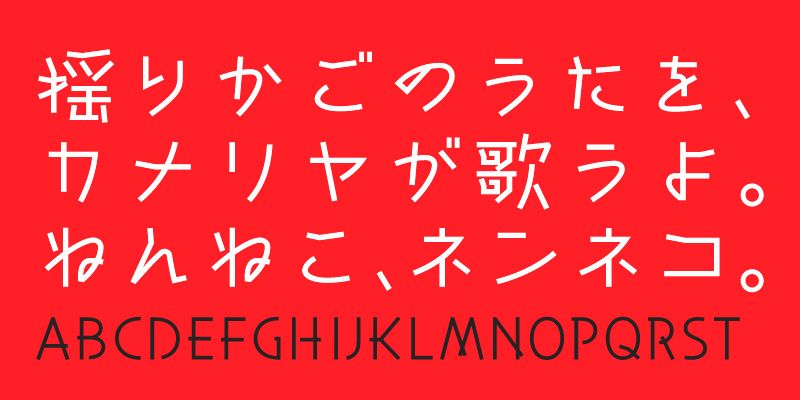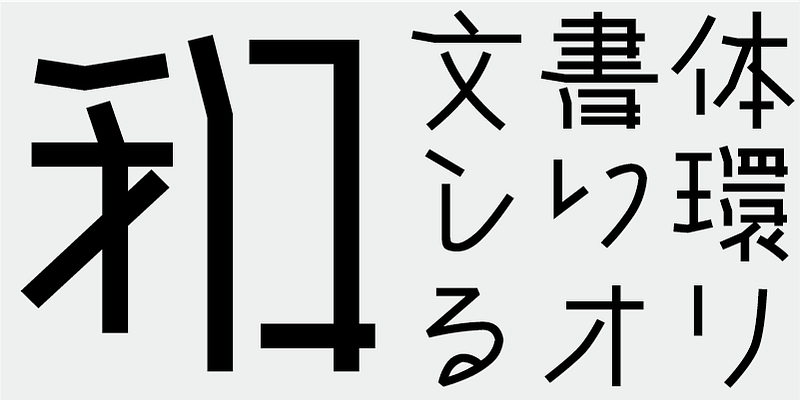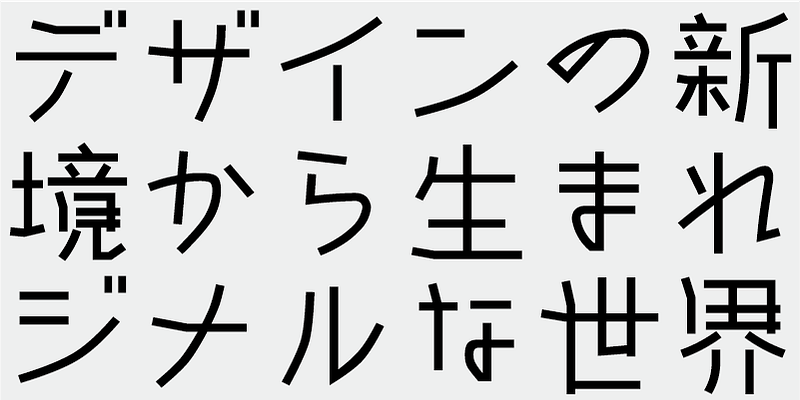
Este tipo de letra tiene un aspecto lineal y está basado en la sensación de los trabajos de mosaicos de madera. Este diseño antiguo tiene algo de innovación y un aire de cuento de hadas. Los caracteres se pueden disponer libremente tanto en dirrección horizontal como vertical. Funciona bien para cartelería y también para la composición de textos de libros ilustrados y libros infantiles.
Esta fuente incluye los 1000 caracteres kanji principales elegidos de tablas de frecuencia de caracteres elaboradas por empresas de periódicos, editoriales e institutos de investigación lingüística, además de 206 caracteres kana y signos de puntuación.
En la producción de fuentes japonesas de hoy en día, los 7000 caracteres del estándar JIS se consideran esenciales. Pero, ¿todas las fuentes realmente necesitan 7000 caracteres? En la época de la fotocomposición, se necesitaban muchos menos caracteres. FONT1000, un grupo de diseñadores de tipos de letra independientes, comenzó con esa sencilla pregunta. Hemos seleccionado el mínimo de 1000 caracteres kanji (ideográficos) necesarios para la composición tipográfica en japonés y nos hemos esforzado en crear tipos de letra y fuentes de forma activa para admitirlos. Este conjunto de 1000 caracteres kanji se seleccionó utilizando datos de frecuencia de caracteres recopilados por empresas de periódicos, editoriales, organizaciones de investigación lingüística, etc., y también incluye caracteres silábicos kana y signos de puntuación. FONT1000 se formó en 2001 con 25 diseñadores y 25 tipos de letra. Hoy tenemos 130 tipos de letra y hemos crecido hasta incluir casi 40 miembros, lo que hace posible trabajar con tipos de letra con más caracteres.